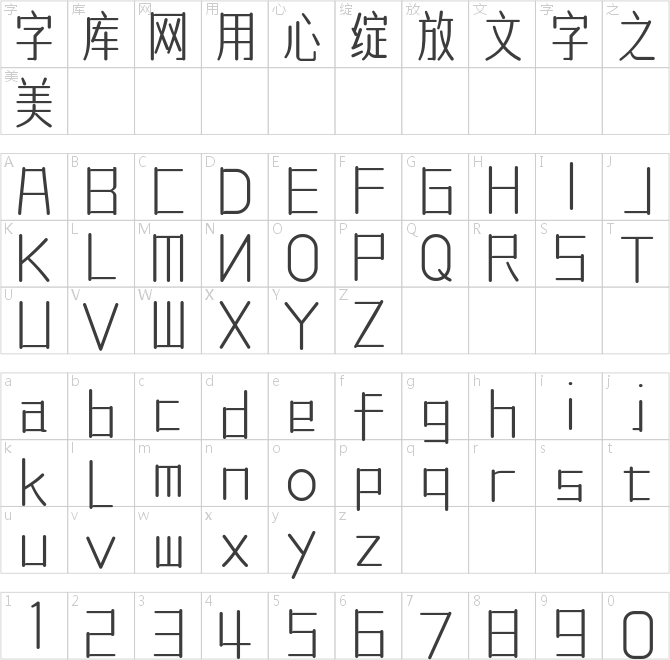
字體名稱: 字體傳奇南安體
字體傳奇南安體
字體傳奇南安體-是字體傳奇網字友-吳金彬設計-字體傳奇編碼完成的一套免費商用字體,字體的起名是吳金彬以他的家鄉南安命名的,他把這款字體,貢獻給大家永久免費商用,也希望大家記住吳金彬和他的家鄉南安。
字體傳奇南安體字體字庫是一款讓人賞心悅目、百看不厭的中文字體,適合各類廣告和產品包裝設計應用,字體大小4.73MB,格式為ttf字體,上傳用戶是……西央,作者/版權方為字體傳奇